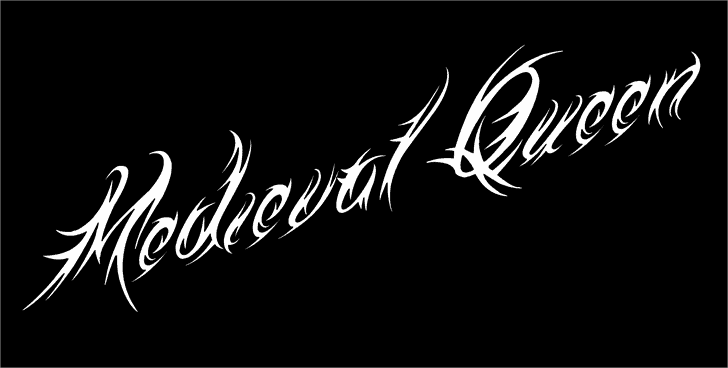
A Medieval Queen é uma elegante fonte script que desperta a fantasia medieval em cada uso. Suas linhas suaves e elegantes parecem ter sido inspiradas na era das cortesãs, com suas curvas delicadas flutuando como um rio veloz através da tela de sua escrita fluida. Perfeita para qualquer projeto que valorize o passado, a Medieval Queen é uma escolha ideal tanto para cartões de aniversário e presentes individuais quanto para criações mais formais, como designs de marca ou cartazes em lojas de arte. Com seu designer, Hamilton, trabalhando cuidadosamente para manter essa alma medieval, você pode ter certeza de que cada detalhe foi cuidadosamente pensado, desde as formas sutis e refinadas até os bordões delicados. Seja para um projeto pessoal ou comercial, a Medieval Queen é uma escolha segura para quem aprecia a elegância dos tempos antigos. Para adquirir licenças de uso comercial dessa fonte, visite o site www.tattoowoo.com ou entre em contato diretamente com Hamilton através do .